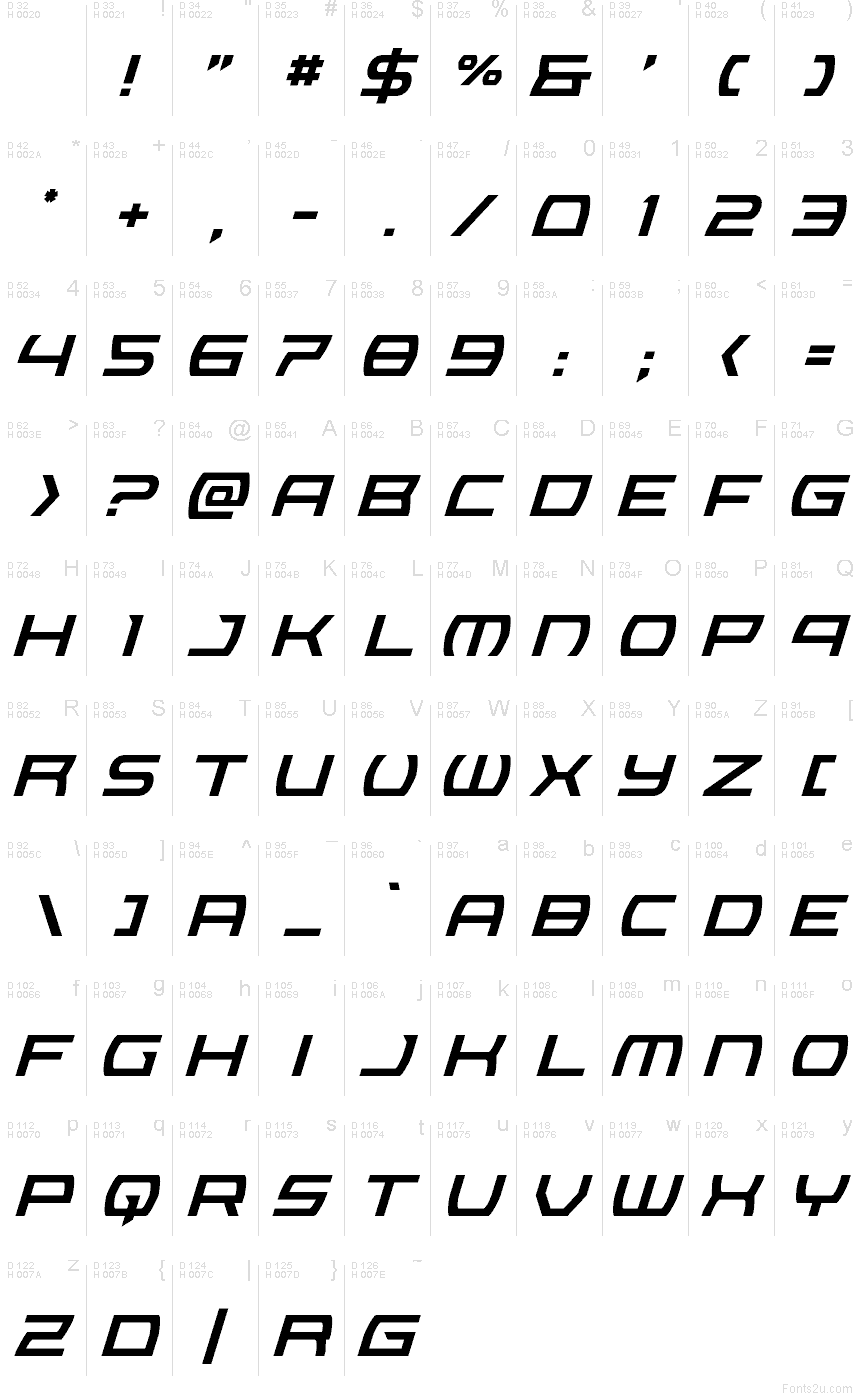
Icemaster Super Italic von Iconian Fonts ist eine kostenlose, futuristische Versalschrift für Displays mit einem schnellen, maschinell wirkenden Neigungswinkel. Die Buchstaben wirken wie aus massiven Blöcken gemeißelt – mit breiten Strichen, beschnittenen Ecken und weit ausladenden horizontalen Linien, die dem Alphabet einen kühlen, aerodynamischen Rhythmus verleihen.
Die Schrift eignet sich hervorragend für Sci-Fi-Poster, Gaming-Logos, Tech-Branding, Titelkarten und Cover-Überschriften, bei denen kurze Wörter diesen eleganten Vorwärtsdrang benötigen. Als kostenloses Font-Design eignet es sich zudem ideal für Monogramme und markante Schlagzeilen, da die Großbuchstaben in einer kompakten Silhouette mit hoher Geschwindigkeit ineinandergreifen, anstatt nur wie eine neutrale Display-Schrift zu wirken.
Icemaster Super-Italic